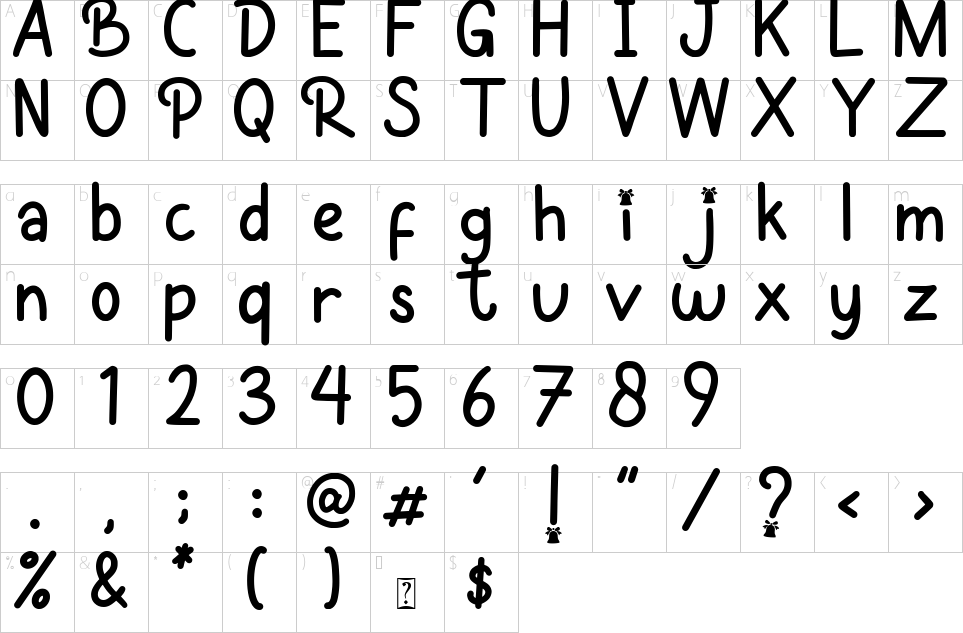
Descubra a fonte Pattia, uma opção fantástica para designers gráficos de todo o Brasil. Esta fonte foi criada por AEN Creative Studio e está disponível gratuitamente tanto para sistemas Windows quanto para Mac. Com seu design elegante e moderno, Pattia oferece uma combinação perfeita de estilo e funcionalidade. Não há dúvida de que esta fonte será uma excelente escolha para projetos digitais em que você deseja destacar um texto com beleza e consistência. Com mais de 1.725 downloads, Pattia já se provou uma fonte confiável, perfeitamente adaptada para qualquer projeto gráfico. Se você está procurando por uma opção de fonte de qualidade para seu próximo projeto, Pattia é definitivamente algo que você deve considerar. Não deixe de experimentar e descobrir por si mesmo qual achará Pattia uma excelente adição à sua biblioteca de recursos gráficos.